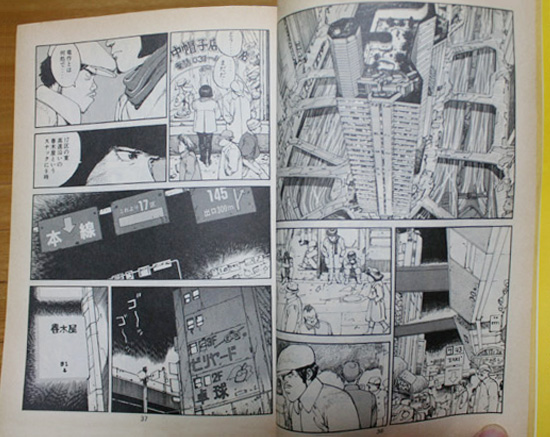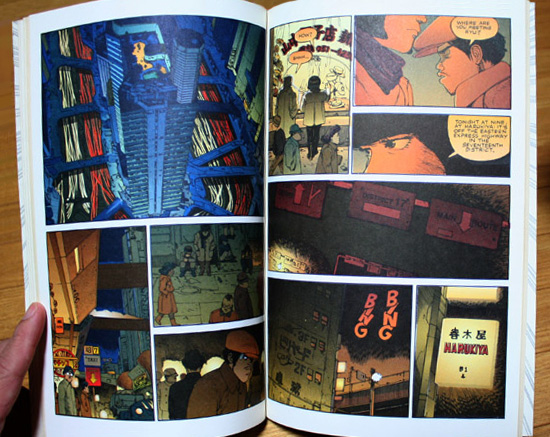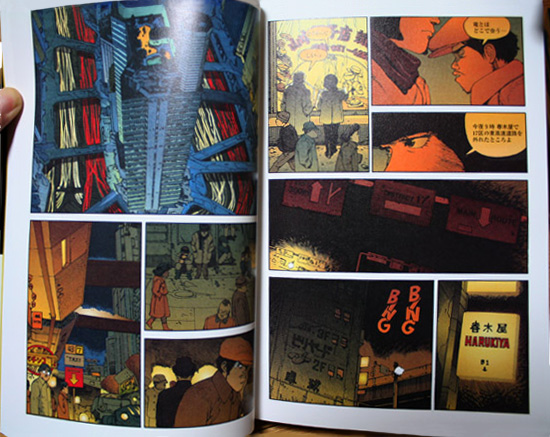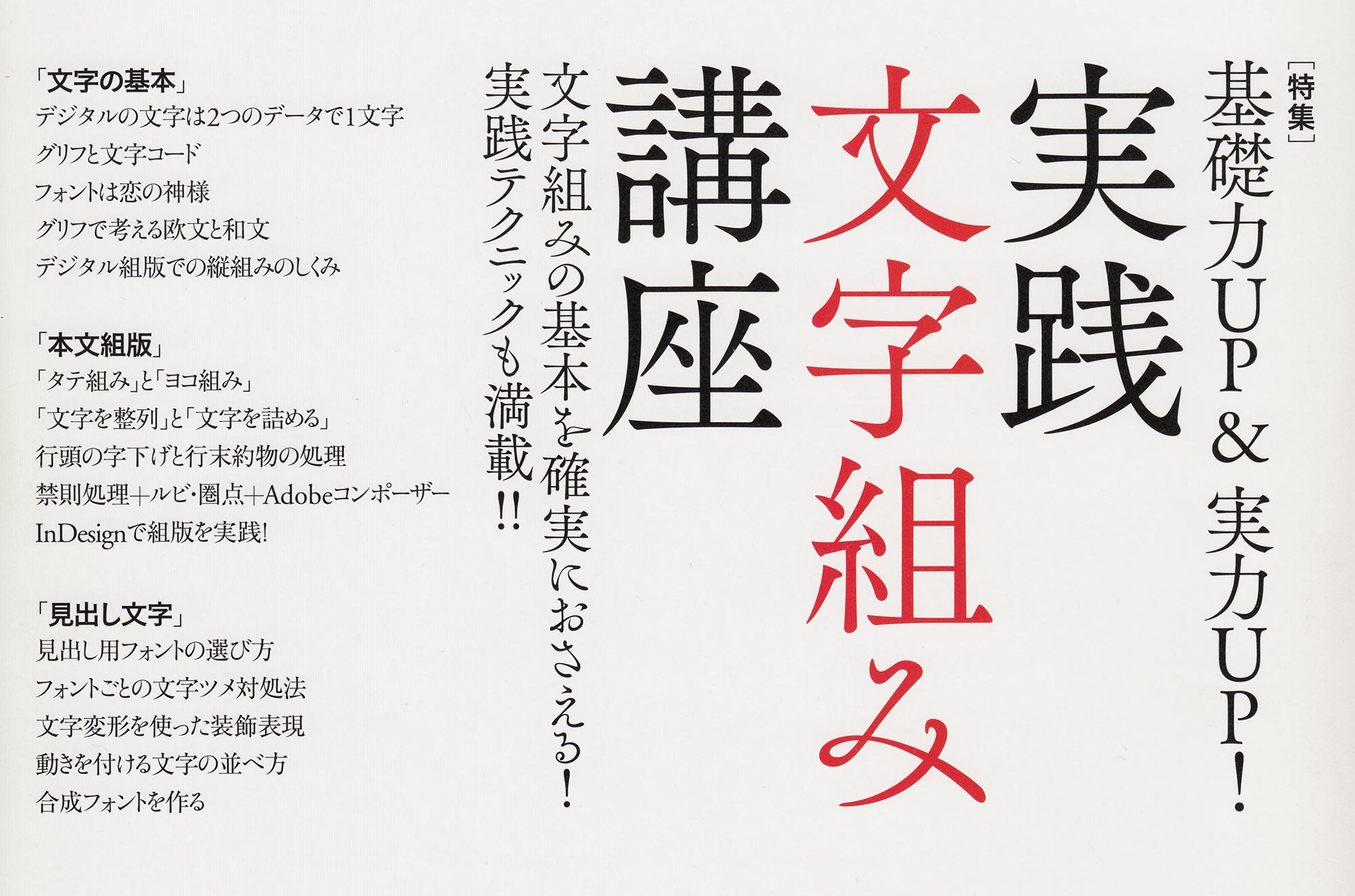
Japanische Typografie – Chaos und Freiheit
Bei Satzarbeiten auf Japanisch treffen verschiedene Schriftsysteme aufeinander: chinesische Schriftzeichen (Kanji 漢字), japanische Silbenschriftzeichen (Hiragana ひらがな und Katakana カタカナ), lateinisches Alphabet, chinesische sowie indisch-arabische Ziffern. Und damit noch nicht genug, Japanisch kann man waagerecht und senkrecht schreiben.
Typografisches Chaos
Japanische Setzer haben es nicht leicht, all diese typografischen Elemente in Einklang zu bringen. Eine homogene, ruhige Satzarbeit, wie man sie sonst aus jeder anderen Sprache kennt, ist im Japanischen nicht zu erwarten. Chaotisch ist wohl der passende Ausdruck für die gegenwärtige Situation in der japanischen Typografie. »Gegenwärtig«, weil sie historisch gesehen nicht immer so regellos gewesen ist wie heute.
Das Chaos begann mit der Verwestlichung des Landes, die Ende des 19. Jahrhunderts mit voller Wucht einsetzte. Das lateinische Alphabet drang immer stärker in den japanischen Alltag ein. Bis dahin besaß auch das Japanische ein recht einheitliches, zum Teil sogar sehr elegantes Erscheinungsbild, es wurde konsequent von oben nach unten, und rechts nach links, geschrieben. Diese klassische Ästhetik der Japaner hat sich z.B. in der japanischen Schreibkunst bis heute erhalten.
Mehrere Versuche im vergangenen Jahrhundert, ein neues Schriftsystem einzuführen (z.B. unter Verzicht auf Kanji nur noch mit Kana zu schreiben oder sogar völlig auf das lateinische Alphabet umzustellen), um das Durcheinander der Schriften zu beenden, kamen nie über das Stadium von Fachdiskussionen hinaus. Der heutige chaotische Zustand der Typografie ist das Ergebnis einer natürlichen Entwicklung und von der japanischen Bevölkerung durchaus gewollt, wobei auch wissenschaftliche Studien an diesem Prozess beteiligt waren. Ich persönlich kann mir nicht vorstellen, dass sich an dieser Situation in absehbarer Zukunft etwas ändert. Und das halte ich auch für richtig.
Es wäre falsch, diese Gegebenheiten nur negativ zu betrachten. Japanische Typografen können unheimlich viel aus der gegenwärtigen Situation machen. Typografisches Chaos in Japan bedeutet für sie auch eine einzigartige typografische Freiheit, die andere Typografen der Welt nicht haben, da sich diese an viel mehr Regeln halten müssen.
Richtungschaos
Auch hierzulande ist mittlerweile allgemein bekannt, dass man japanische Bücher hinten aufschlägt und Seite für Seite nach vorn blättert, wenn Texte von oben nach unten geschrieben sind, weil die Zeilen bei senkrechter Schreibweise von rechts nach links verlaufen. Japanische Manga in deutschen Buchhandlungen sind gute Beispiele. Sie werden »von hinten nach vorn« geblättert, weil die japanischen Texte, die ins Deutsche übertragen wurden, im Original senkrecht gesetzt waren, und aus ästhetischen wie Kostengründen auf einen Seitenumbau* verzichtet wurde. Aber scheinbar haben die deutschen meist jugendlichen Leser damit keine Probleme und so lässt sich vielleicht sogar sagen, dass sich auch in Europa die Lesegewohnheiten ändern.
In Japan gibt es zwei Richtungen des Textflusses. Man liest entweder von oben nach unten oder von links nach rechts. Oft werden die beiden Satzarten auf derselben Seite, Doppelseite oder im ganzen Buch durchweg gemischt. In welche Richtung so eine Publikation geblättert wird, hängt vom Inhalt ab. Es gibt keine klaren Regeln dafür und Japaner sind gewohnt, sich sofort auf die ständig wechselnde Leserichtung einzustellen.
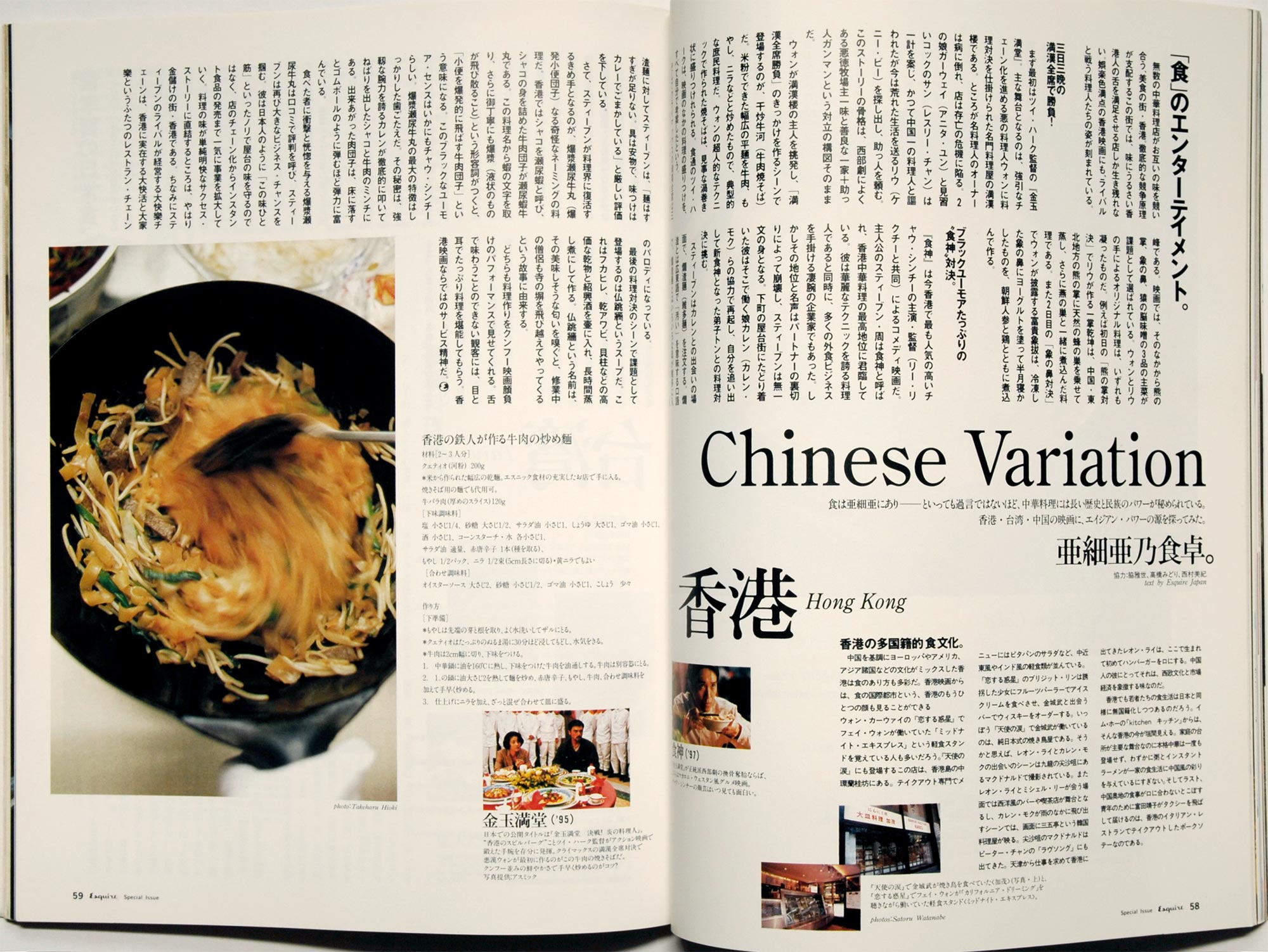
Wo fängt man an zu lesen?So sieht eine ganz gewöhnliche Doppelseite einer Zeitschrift aus. Die meisten Zeitschriften in Japan werden von rechts nach links geblättert, selbst wenn die Mehrheit der Texte waagerecht gesetzt ist.
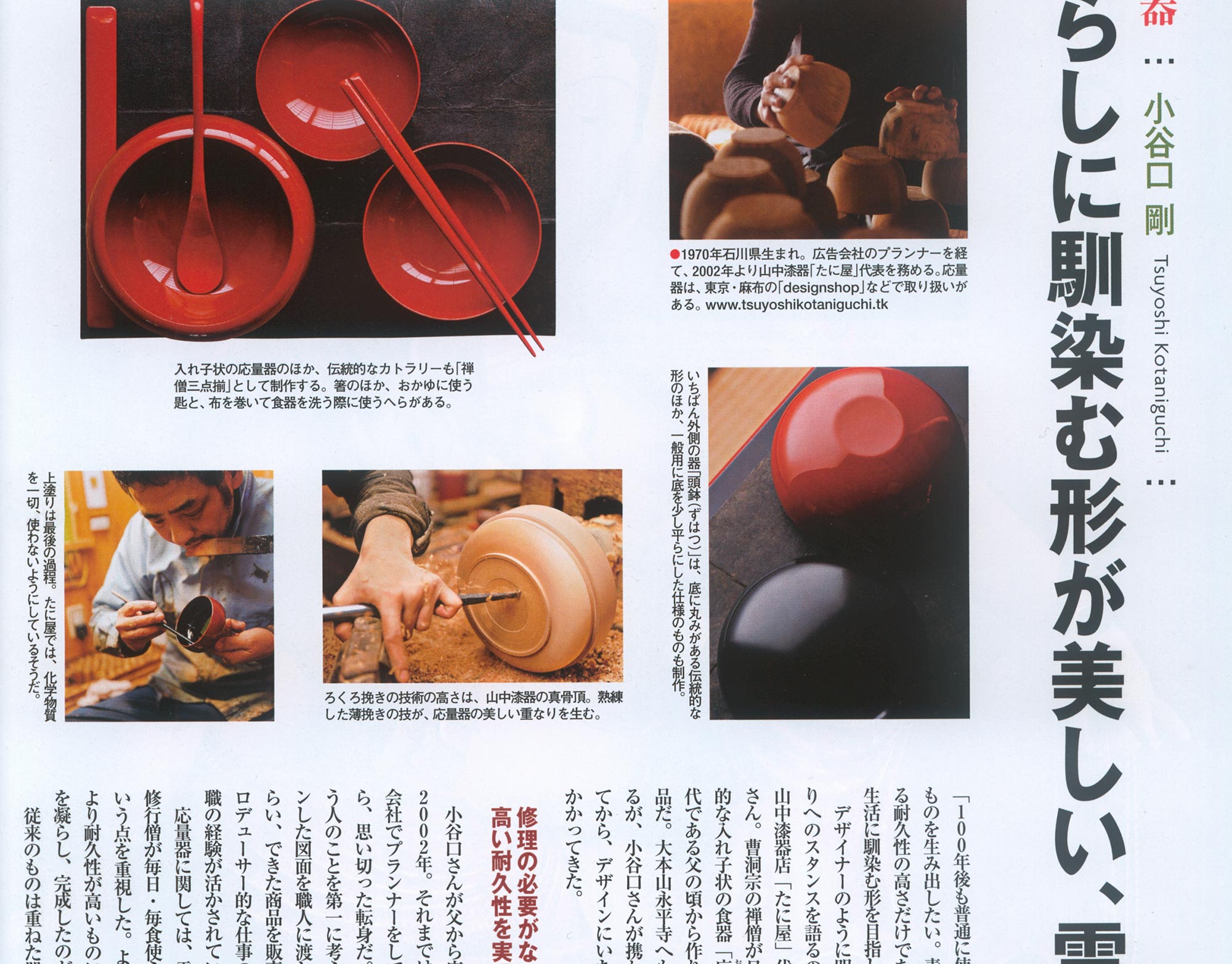
Mal unten, mal links.Dieser Ausschnitt aus einer Zeitschrift zeigt, wie flexibel japanische Bildunterschriften platziert werden können.
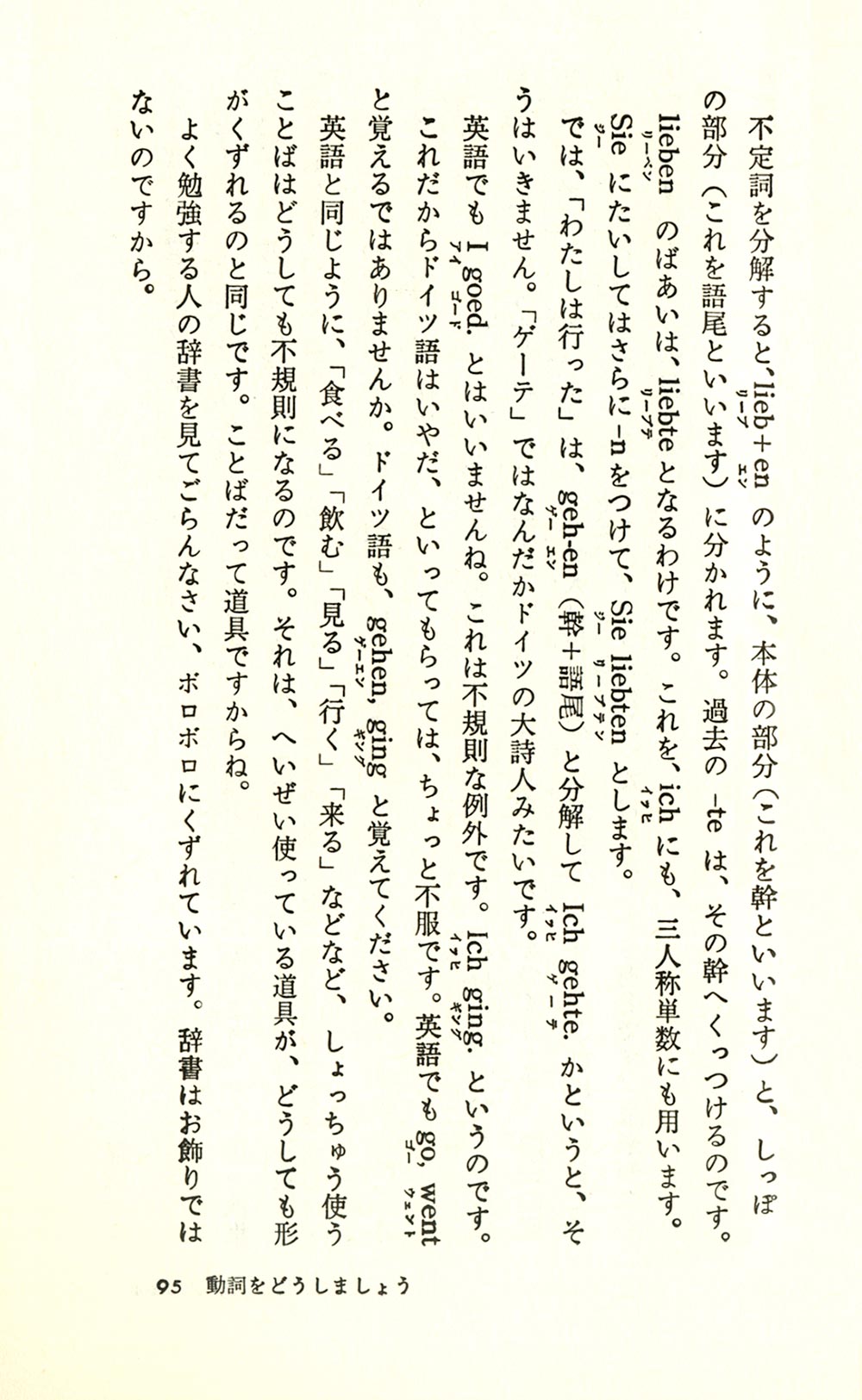
Verdrehte Buchstaben.Seite aus einem 1964 erschienenen Lehrbuch für Deutsch, das im Erzählstil geschrieben ist. Buchtexte werden meist senkrecht gesetzt, bei Romanen oder Erzählungen ist das fast ausschließlich der Fall. Normalerweise werden die lateinischen Buchstaben im senkrechten Satz um 90 Grad gedreht gesetzt. Aber in diesem Beispiel wurden kurioserweise auch drei Kanji, nach »geh-en« in der fünften Zeile von rechts, um 90 Grad gedreht. Ebenfalls gedreht gesetzt wurden die ganz kleinen »Ruby« genannten Schriftzeichen neben (eigentlich unter) den lateinischen Buchstaben.
Übrigens sind »Ich gehte.« und »I goed.« keine Druckfehler sondern Beispiele für falsche Formbildung.
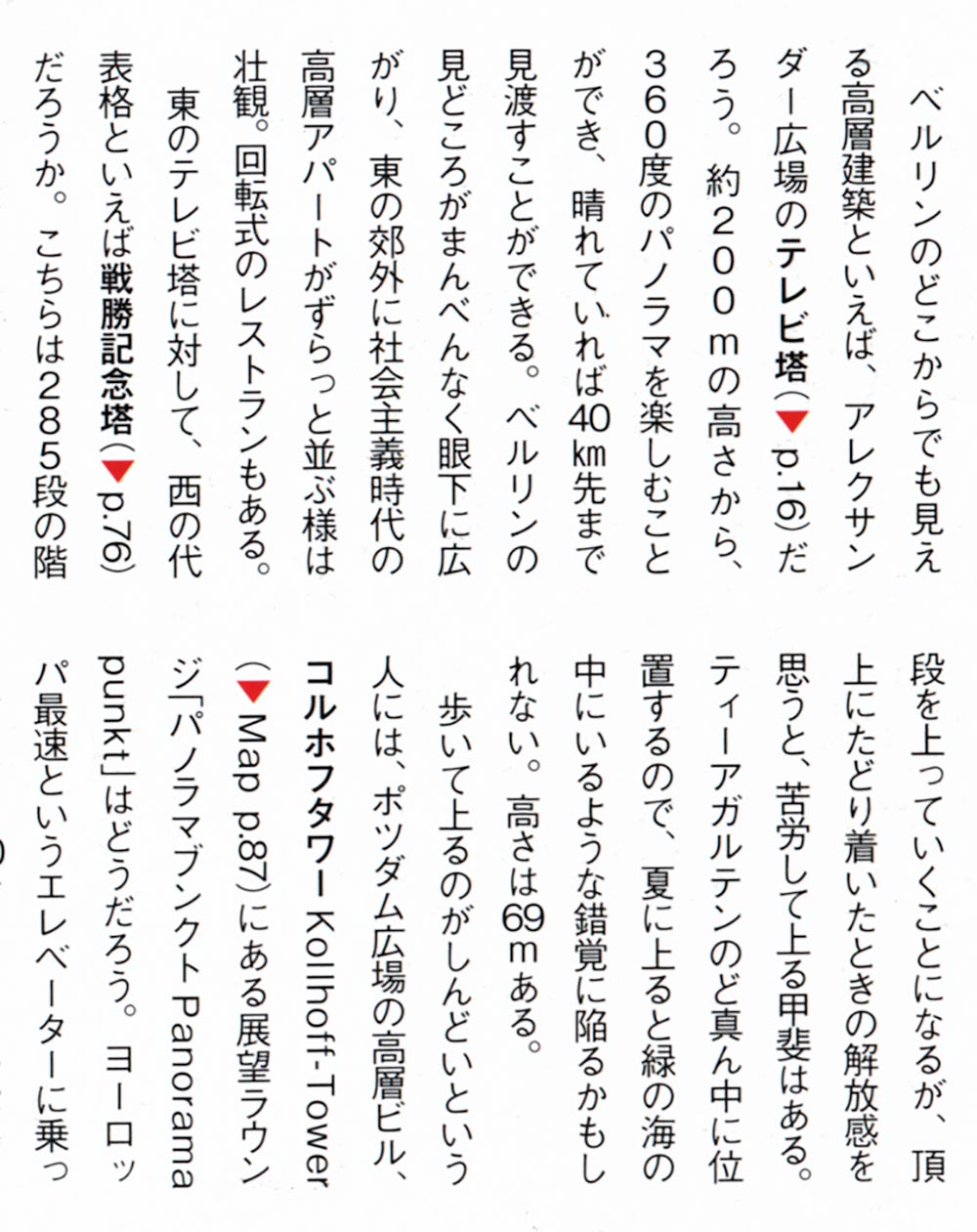
Wandlungsfreudige Ziffern.Ausschnitt aus einem Berlin-Reiseführer: Besonders interessant ist, wie Ziffern und lateinische Buchstaben gesetzt sind. Zahlen mit bis zu zwei Ziffern wurden horizontal nebeneinander gesetzt (40 km, 60 m), ab drei Ziffern nicht mehr (200 m, 360). Die Seitenhinweise sind um 90 Grad gedreht (p.16, p.76, p.87). Trennstriche werden im Japanischen oft gar nicht gesetzt und auch hier bei »Panoramapunkt« einfach weggelassen. Übrigens ist das Kilometer-Zeichen »km« im japanischen Font als ein eigenes Zeichen vorhanden.
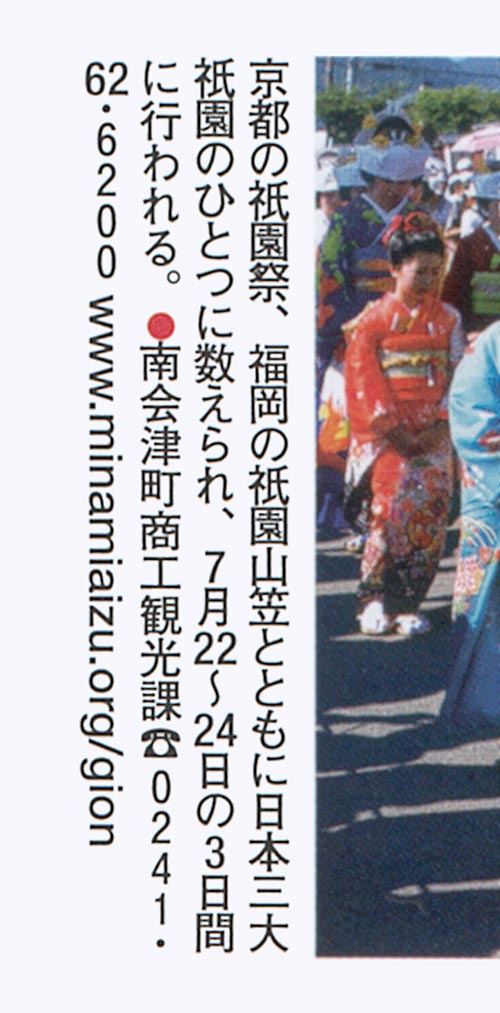
Priorität Senkrecht.Die Telefonnummer kommt Europäern sicher eigenartig vor. Man hätte sie genauso gut auch um 90 Grad gedreht setzen können, wie die URL daneben. Aber so ist es in Japan durchaus üblich. Offensichtlich ist es Japanern lieber, wenn im senkrechten Lesefluss die Zeichen nicht gekippt werden.
Das zweite Bild (auf den Pfeil klicken) zeigt ebenfalls die gleiche Doppelseite aus der Reimport-Ausgabe auf Japanisch. Ungewöhnlich daran ist, dass die Texte horizontal gesetzt sind, noch interessanter, dass die Dialoge aus dem Englischen zurückübersetzt wurden und mit denen der Originalausgabe nicht identisch sind. Ha!